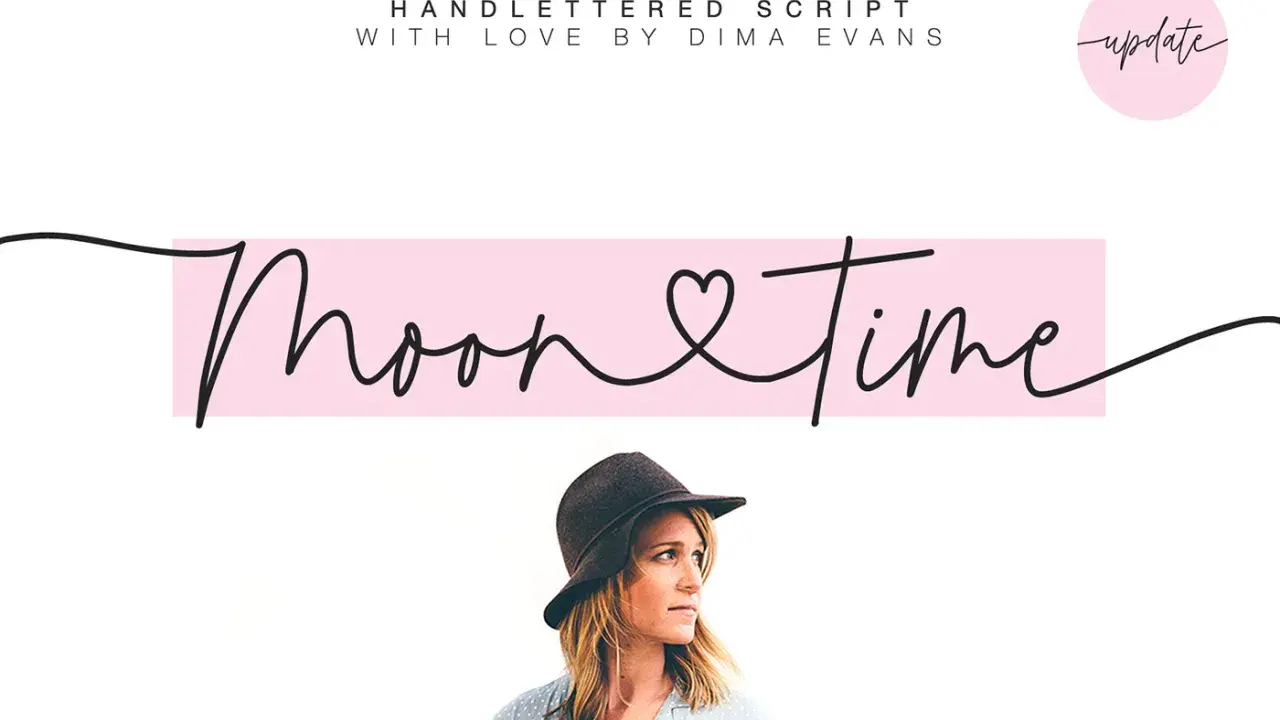
Moontime font - elegancki script. Jak go używać w projektach?
Ręcznie pisany font "Moon time" z sercem w środku, obok napisu "update".
Moontime font to elegancki krój pisma o wyraźnym charakterze kaligraficznym, który najlepiej pracuje tam, gdzie tekst ma budować nastrój, a nie tylko przekazywać informację. W tym artykule pokazuję, czym wyróżnia się ten font, gdzie faktycznie daje najlepszy efekt, jak używać go w druku i narzędziach online oraz kiedy lepiej wybrać spokojniejszą alternatywę. To ważne, bo przy takich krojach jeden dobry wybór potrafi podnieść jakość projektu, a jeden zły szybko go obniża.
Najważniejsze rzeczy o tym kroju, zanim trafi do projektu
• To dekoracyjny script z kaligraficznym rytmem, więc działa najlepiej w krótkich komunikatach.
• Najmocniej wygląda w logo, zaproszeniach, etykietach, okładkach i grafikach promocyjnych.
• Ma ozdobne swashe i warianty liter, które pomagają zbudować bardziej dopracowany skład.
• Warto sprawdzić polskie znaki, kerning i zachowanie fontu w konkretnej aplikacji przed publikacją.
Jak wygląda ten krój i jaki daje efekt
To nie jest neutralny font roboczy ani klasyczny bezszeryfowy skład. Moontime działa jak script, czyli krój stylizowany na pismo odręczne, z miękkim rytmem, płynnymi połączeniami i ozdobnymi zakończeniami. Na materiałach prezentacyjnych widać też dodatkowe elementy, które realnie podnoszą użyteczność: swashe, warianty wielkich i małych liter, monogramy oraz wsparcie dla wielu języków europejskich.
Na Behance twórca pokazuje ten kierunek bardzo jasno: to ma być krój elegancki, nowoczesny i lekko „premium” w odbiorze. W praktyce daje to efekt bardziej osobisty niż zwykły display font, ale mniej formalny niż klasyczna kaligrafia piórem. Ja traktuję taki krój jak akcent, nie jak bazę całego layoutu. Gdy dostaje oddech, wygląda świetnie. Gdy jest ściśnięty, traci cały urok.
Najważniejsze jest więc nie tylko to, jak wygląda sam alfabet, ale też jak zachowuje się w kompozycji. Ten rodzaj pisma lubi przestrzeń, kontrast i spokojne otoczenie typograficzne. Właśnie dlatego warto od razu przejść od estetyki do zastosowań, bo tam wychodzi, czy krój naprawdę pracuje na projekt.
Gdzie sprawdza się najlepiej
Największą wartość ten font daje tam, gdzie tekst ma przyciągać wzrok w jednej chwili. Nie wybierałbym go do długich akapitów, ale w krótkich hasłach potrafi zrobić dokładnie to, czego oczekuje się od eleganckiego skryptu: dodać lekkości, ruchu i wrażenia ręcznego dopracowania.
Zastosowanie Dlaczego działa Kiedy uważać
Logo i identyfikacja marki Buduje wrażenie premium, butikowości i indywidualnego charakteru. Nie sprawdzi się przy markach, które chcą być chłodne, techniczne albo bardzo korporacyjne.
Zaproszenia i papeteria Świetnie wygląda w krótkich formach ślubnych, okolicznościowych i prezentowych. Przy zbyt małym formacie swashe zaczynają się zlewać, a czytelność spada.
Etykiety i opakowania Dodaje rękodzielniczego, bardziej osobistego charakteru. Na małych etykietach trzeba sprawdzić, czy cienkie fragmenty nie giną po druku.
Grafiki do social media Dobry do cytatów, nagłówków i pojedynczych słów, które mają „zatrzymać kciuk”. Nie powinien konkurować z nadmiarem dekoracji, tła i efektów.
Okładki, plakaty, materiały promocyjne Tworzy mocny punkt skupienia i podnosi wrażenie jakości. Warto zostawić dużo światła wokół liternictwa, inaczej efekt będzie ciężki.
W opisie produktu na Creative Market wprost widać, że ten krój jest kierowany do projektów logo, druku, pamiątek, merchu i grafik do internetu. To dobry trop: Moontime nie jest fontem „do wszystkiego”, ale w swoich naturalnych zastosowaniach wypada bardzo przekonująco. Z punktu widzenia osoby pracującej przy materiałach drukowanych najważniejsze jest jedno pytanie: czy tekst ma być ozdobą, czy musi nieść dużo treści. Jeśli ma nieść dużo treści, ten krój schodzi na dalszy plan.
To prowadzi do kolejnego praktycznego tematu: jak ustawić go tak, żeby nie stracić jakości w druku i w aplikacjach, w których projektuje się na szybko.
Jak używać go w druku i w narzędziach online
Przy takich krojach zaczynam od prostego założenia: mniej tekstu, więcej przestrzeni. To naprawdę robi różnicę. Jeśli projekt ma wyglądać dobrze, trzeba dać literom miejsce, a nie wciskać je w ciasny blok. W praktyce najlepiej działa krótki napis, pojedyncze hasło albo nazwa marki, a nie rozbudowany opis.
1. Zacznij od krótkiej treści, najlepiej 1-4 słów. Dłuższe zdania szybko tracą lekkość.
2. Ustaw większy rozmiar niż w zwykłym kroju. Do druku zwykle testuję co najmniej 24-32 pt, a w grafice ekranowej zaczynam od ok. 48 px wzwyż.
3. Dopilnuj odstępów. Tracking ustaw delikatnie, najczęściej w okolicach 0 do +20, a line-height trzymaj raczej blisko 1.1-1.3.